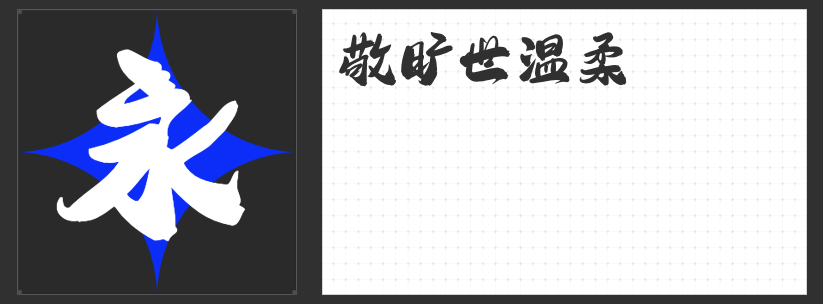
国潮当道:四款造字侠系列字体,解锁东方美学新表达
当传统书法与现代设计碰撞,国潮字体以独特的文化基因与视觉张力,成为品牌叙事与视觉传达的点睛之笔。造字侠系列四款字体,以侠义精神为内核,融合书法笔意与当代审美,为设计注入刚柔并济的东方气韵。
一、造字侠伏魔简繁 传神
以“伏魔”为名,这款字体以浓墨重彩的笔触勾勒出雷霆万钧之势。笔画粗细对比强烈,横竖转折如刀劈斧凿,而“勾、提、挑、捺”等细节则夸张延展,似侠客挥剑时衣袂翻飞的动态定格。单字结构收放自如,疏密间暗藏节奏,既保留楷书的中正骨架,又以飞白与墨韵强化视觉冲击力,适用于需要力量感与仪式感的国潮场景。
二、造字侠仗剑简繁 传神
“仗剑”二字,道尽这款字体的侠骨风范。字形稳重如山,笔画却张扬如风——折、提、钩等部首以干净利落的折角收束,似剑锋出鞘的寒光;横画微扬的弧度与竖画的挺拔形成张力,整体如侠客仗剑天涯的剪影。其设计巧妙平衡了传统书法的韵律与现代设计的简洁,适合传递洒脱不羁的国潮态度。
三、造字侠永刚漆书简繁
灵感源自传统漆书工艺,这款字体以厚重如漆的笔画奠定沉稳基调,撇捺却如流水般从容舒展,赋予字形刚柔并济的灵性。框架醒目而字型端庄,笔画间保留毛笔手书的自然毛边,既保留书法的人文温度,又通过统一的风格强化视觉识别度。其百搭属性使其成为包装、广告、平面设计中的“安全牌”,轻松驾驭各类国潮主题。
四、造字侠侠道简繁
以“侠道”为魂,这款字体以饱满的字形与松弛的笔意诠释东方侠者的自由精神。回锋收笔处略带顿挫,转折处笔画突显如骨节嶙峋,飞白与墨渍的适度夸张更添桀骜不驯的气质。整体布白均匀却暗藏变化,节奏如鼓点般鲜明,适合需要突破常规、彰显个性的国潮设计,让文字本身即成为视觉焦点。
造字侠系列字体,以侠义文化为锚点,将书法的意境美与设计的功能性完美融合。无论是追求力量感、潇洒感、稳重感还是叛逆感,这四款字体都能以独特的笔墨语言,为设计注入穿越时空的东方魂。